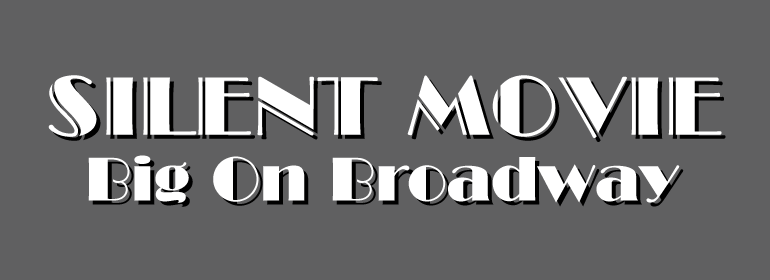
Monotype Broadway™
Monotype Broadway™,这款字体结构工整、笔画清晰,兼顾美观与易读性,适用于标题、正文、海报、包装、LOGO 等多种场景。字形优雅稳定,风格百搭耐看,适配日常排版与创意设计,让文字呈现更舒适、更具质感。Monotype Broadway™一笔一画,皆是细节,以均衡的比例、流畅的线条打造舒适视觉体验,字形端正大气,风格简约现代。无论是商业设计、品牌宣传还是日常排版,都能轻松驾驭,让文字更有格调与力量。Monotype Broadway™字体下载。
字体品牌: Monotype 设计师:Benton,Morris Fuller 字体分类:衬线体 字体属性:外文 字符集:Unicode 发布时间: 2018